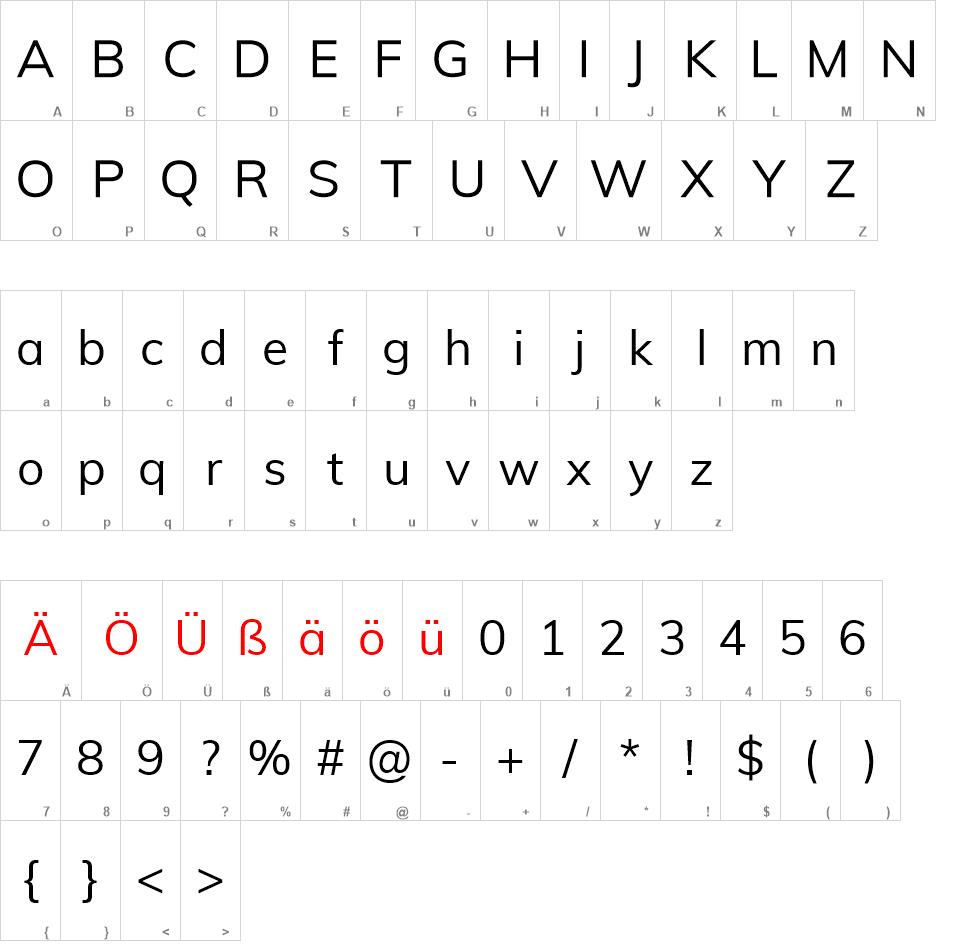
Muli
Muli font
Muli Font ist eine minimalistische Sans Serif. Muli wird hauptsächlich als Bildschirmschrift verwendet, kann aber auch als Textschrift verwendet werden. Muli ist so konzipiert, dass es von Webbrowsern auf Desktops, Laptops und mobilen Geräten frei verwendet werden kann.